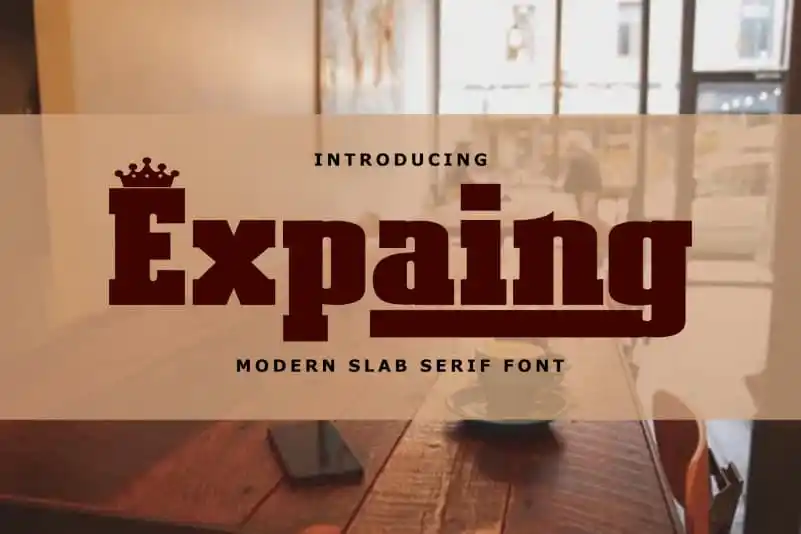
Expaing Slab Serif Font – Fonte Grátis
Expaing Slab Serif Font
A font Expaing Slab Serif é uma escolha ideal para aqueles buscando um estilo robusto e sofisticado que se destaca no design. Com seu peso forte, essa fonte é perfeita para criar gráficos memoráveis e elegantes, especialmente em elementos como logomarcas e branding. Suas características extensivas incluem letras maiúsculas, minúsculas, números e símbolos, além de suporte multilíngue que permite uma aplicação global. Ideal para qualquer projeto gráfico que exige elegância, a Expaing Slab Serif é especialmente adequada para desenhos de moda, design de casamentos, posts nas redes sociais, anúncios e embalagens de produtos. Ela também se destaca no design de etiquetas, fotografia e em qualquer projeto gráfico que busque uma aparência robusta e sofisticada. Seja você um designer profissional ou iniciante, a Expaing Slab Serif oferece tudo o que precisa para trazer seus projetos ao próximo nível. Esta font será definitivamente uma escolha inteligente para se tornar parte da sua coleção de ferramentas de design gráfico.